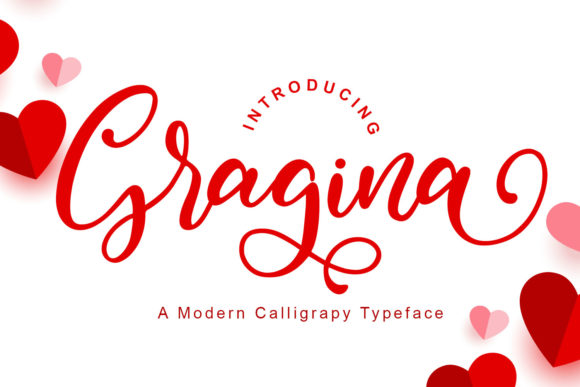
Gragina - это плавный рукописный шрифт, описанный элегантным прикосновением, идеально подходящий для ваших любимых проектов.
Влюбитесь в его невероятно выразительный и неподвластный времени стиль и используйте его для создания эффектных дизайнерских решений!